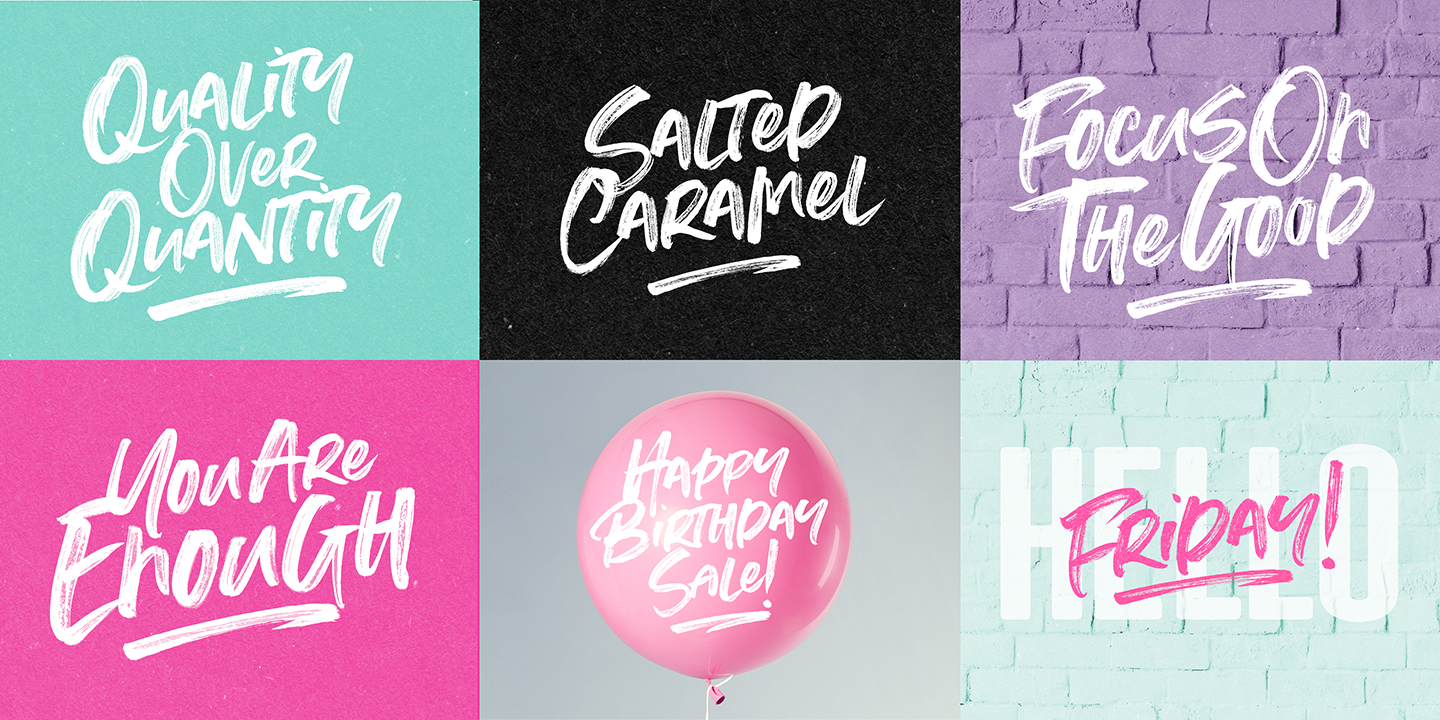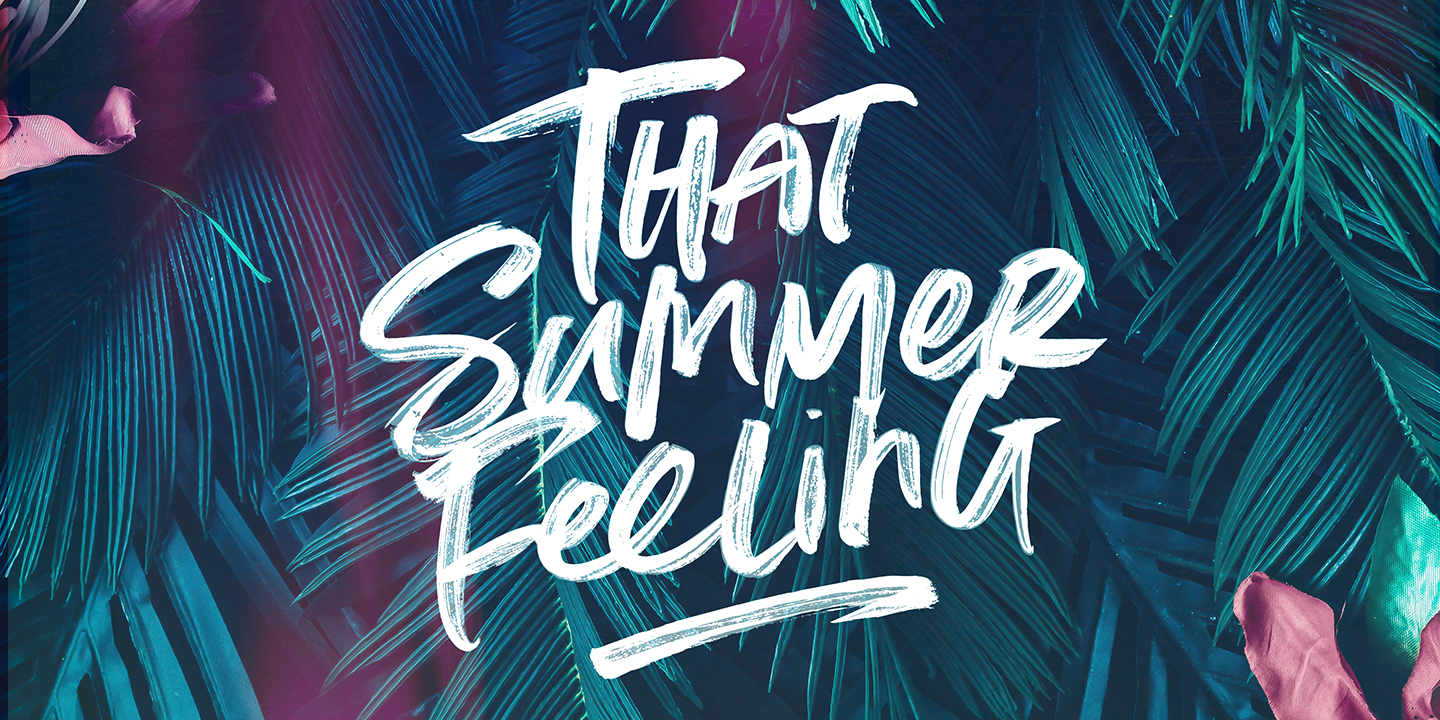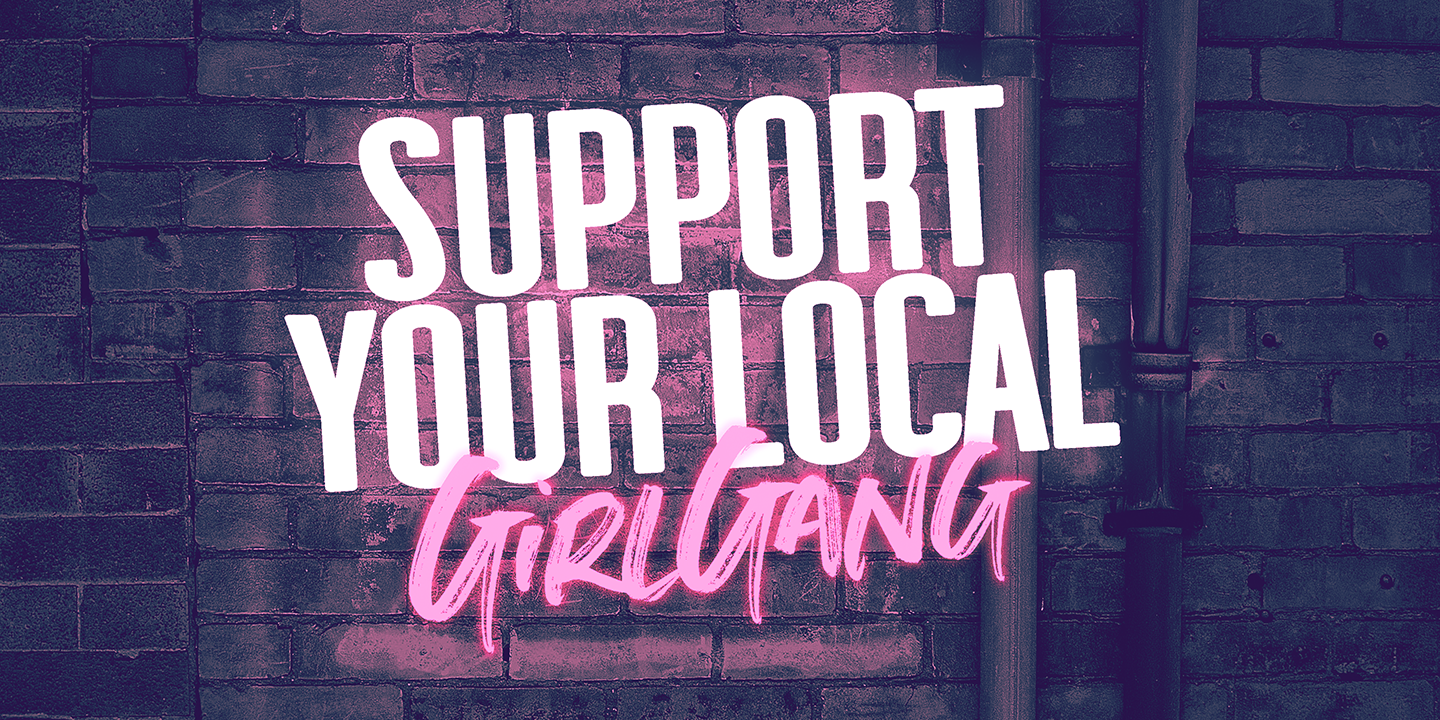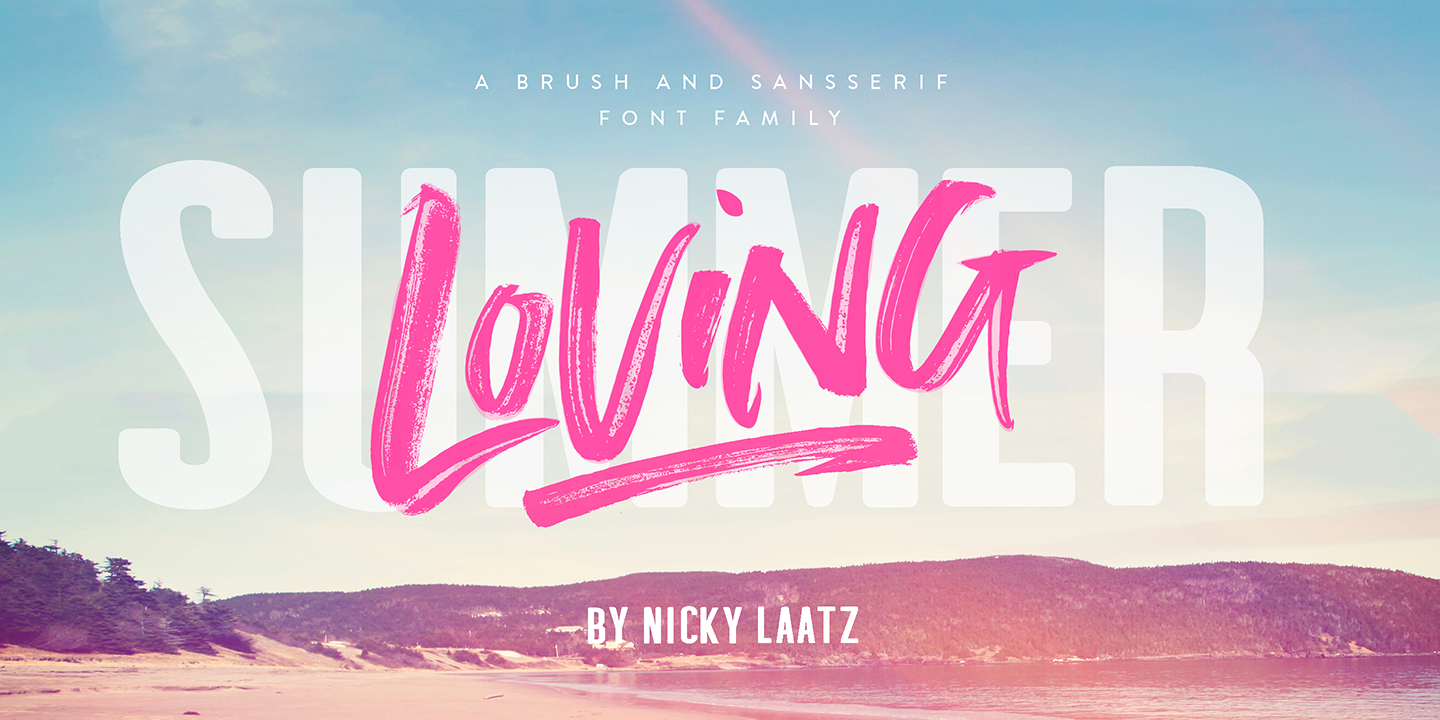
Summer Loving Font Collection là bộ font khá đẹp có giá 24$ bao gồm 3 font với các đường nét cọ vẽ tuyệt đẹp. Font được thiết kế tỉ mỉ mang lại cho bạn trải nghiệm thiết kế tuyệt vời.
Font chưa được Việt Hóa nhưng bao gồm đầy đủ glyphs do đó bạn có thể thêm dấu dễ dàng.